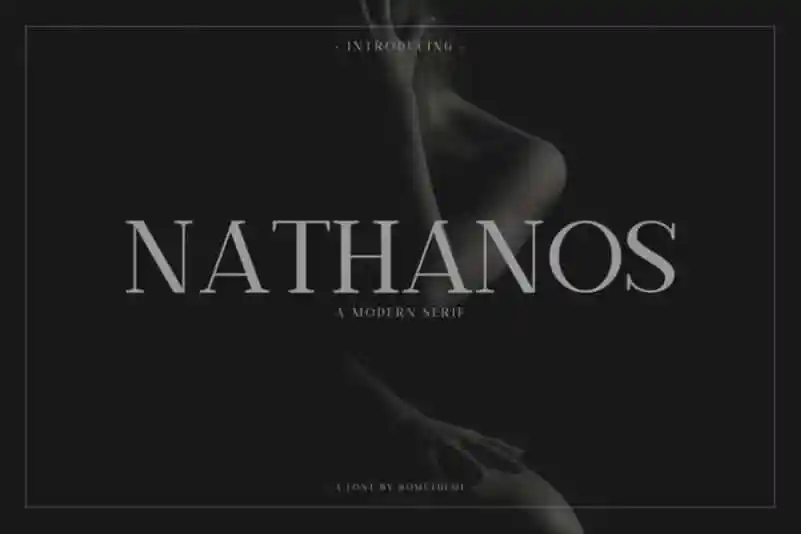
Nathanos Serif Font é uma escolha perfeita para quem busca uma tipografia com um toque elegante e sofisticado. Introduzida pelo 99designs, esta fonte vem com letras maiúsculas, números e uma ampla gama de pontuação, que lhe permite criar designs variados e atraentes. Este estilo serif se harmoniza perfeitamente com estilos manuscritos ou assinaturas, tornando-o ideal para os mais diversos projetos de design gráfico. Nathanos é um alinhamento sólido para criações como assinaturas, cabeçalhos, títulos, capas de livros, logotipos, layouts web, convites, apresentações, panfletos e até mesmo cartões de nome. Suporte a múltiplas plataformas inclui tanto os mais tradicionais quanto as mais modernas, garantindo que sua marca seja vista perfeitamente em qualquer ambiente digital ou impresso. Além disso, a fonte vem equipada com um estilo elegante e sofisticado, tornando-a uma escolha inteligente para aqueles buscando qualidade e coerência em seus projetos gráficos.